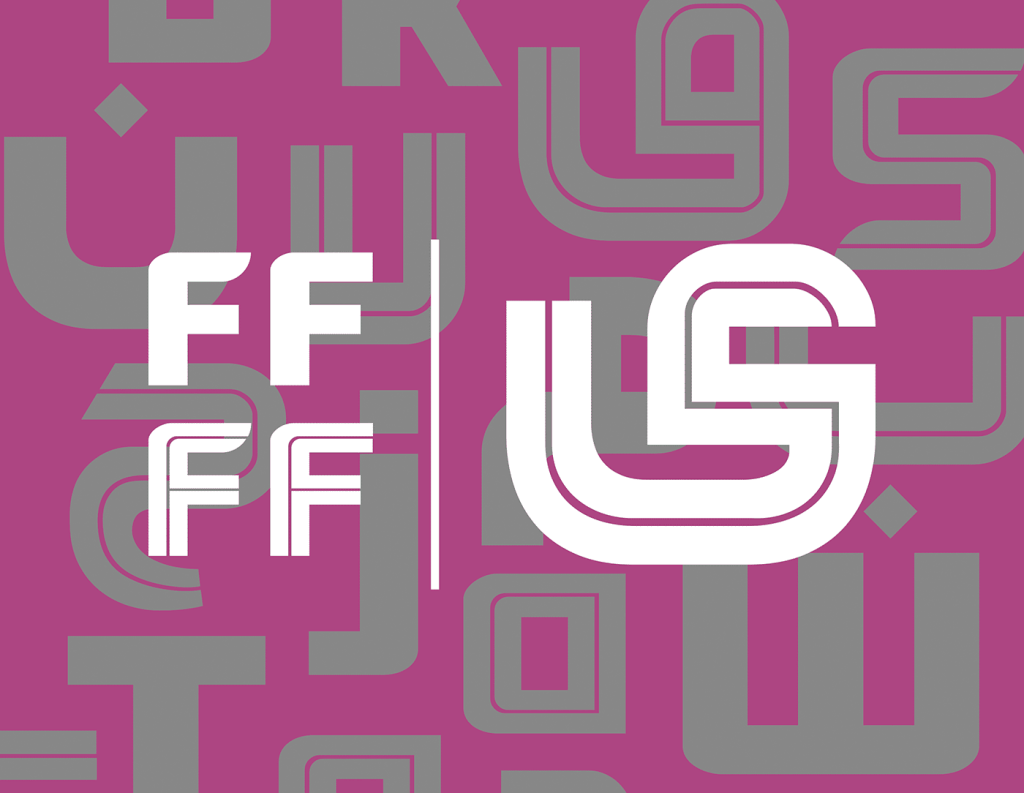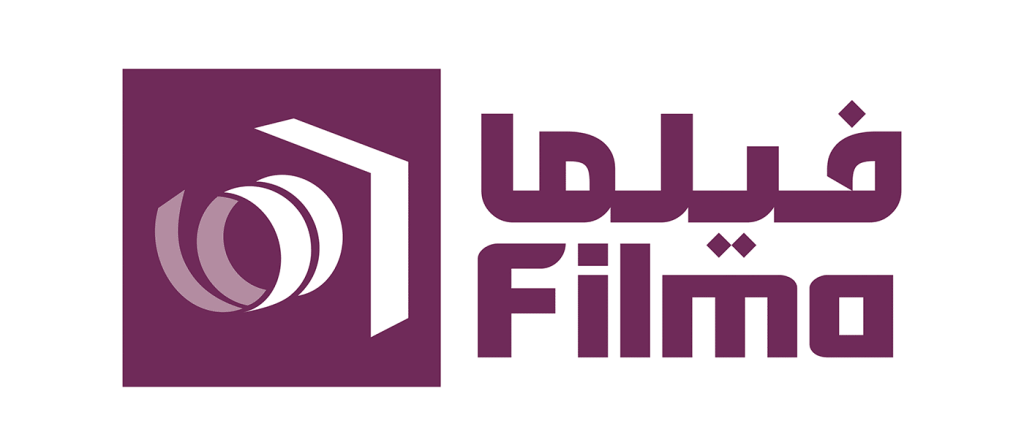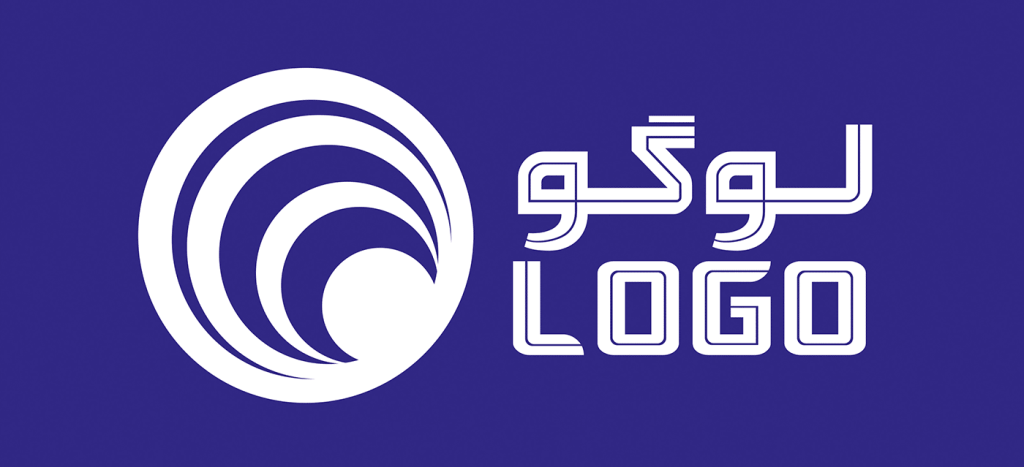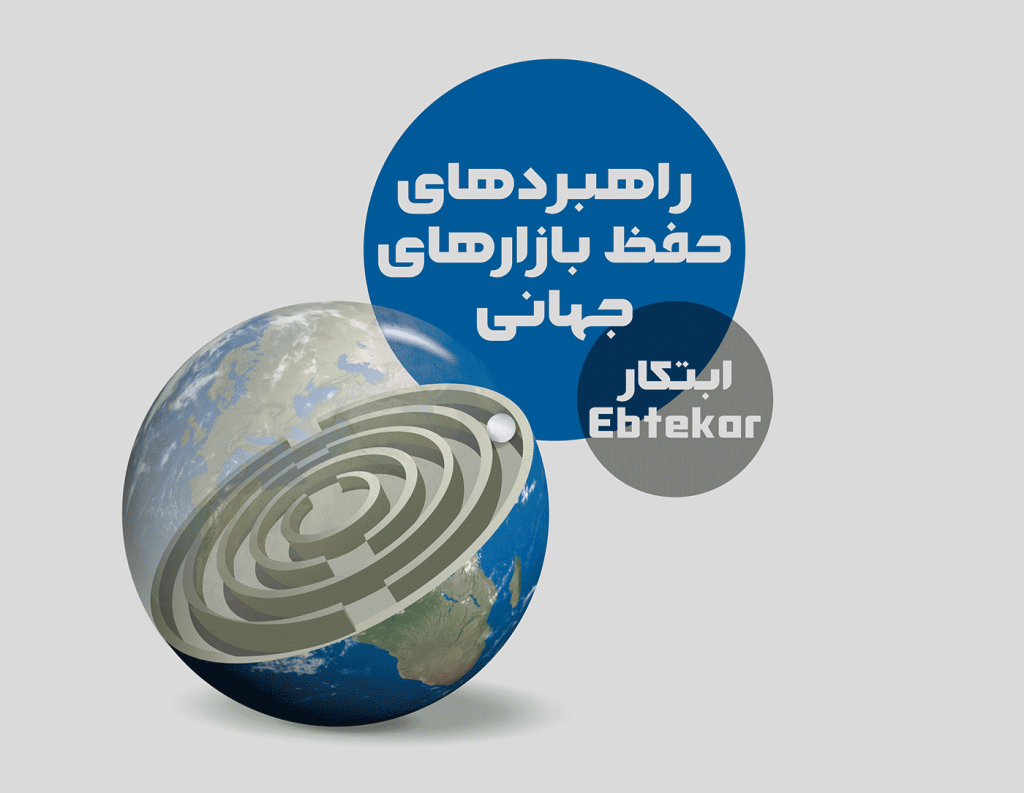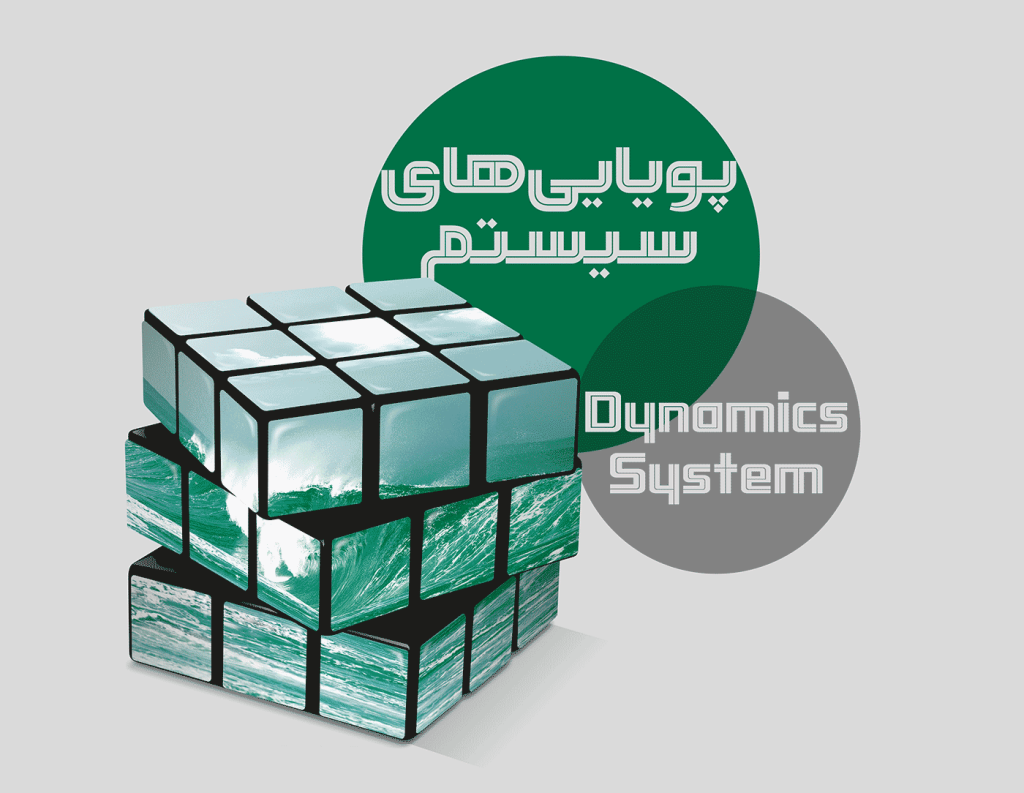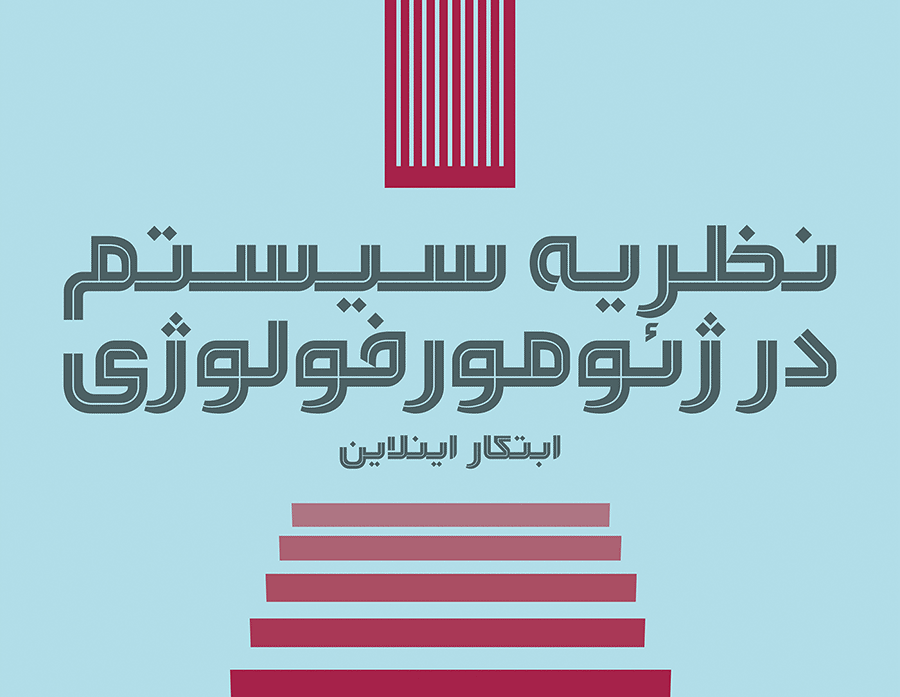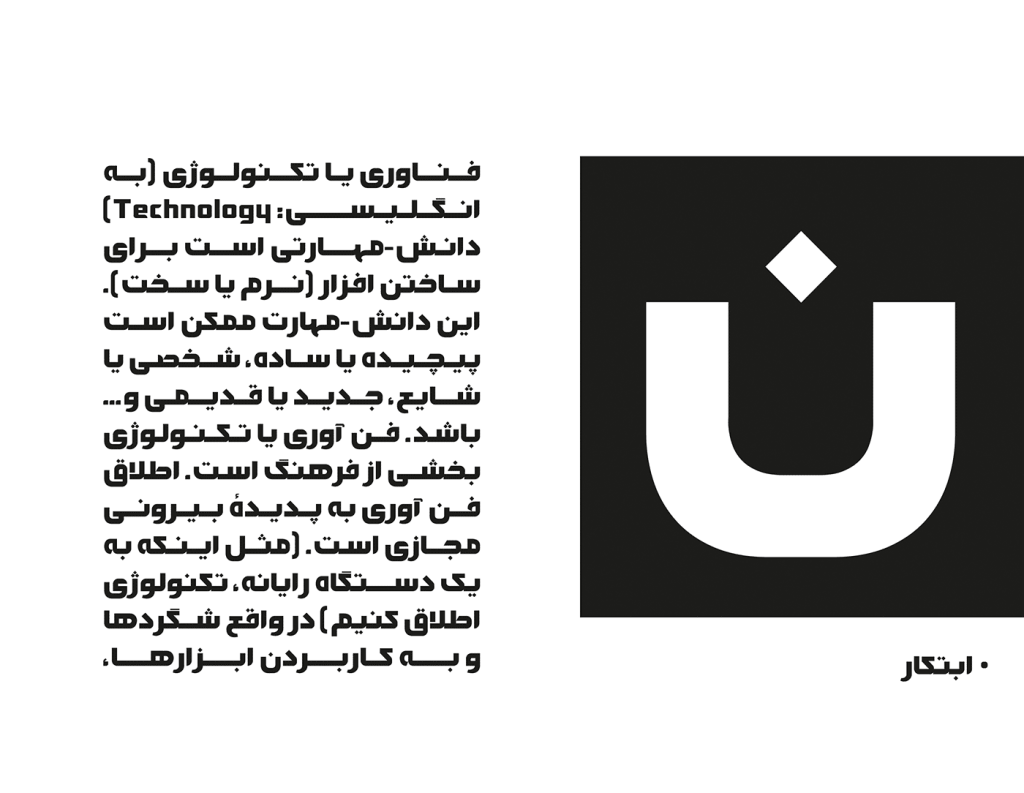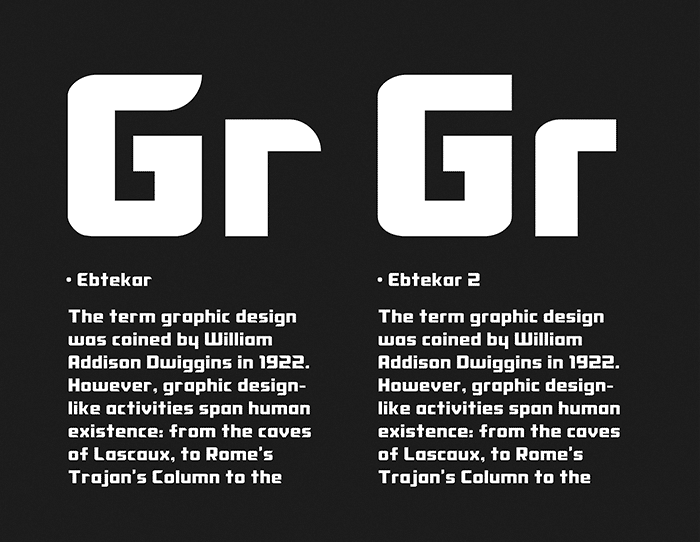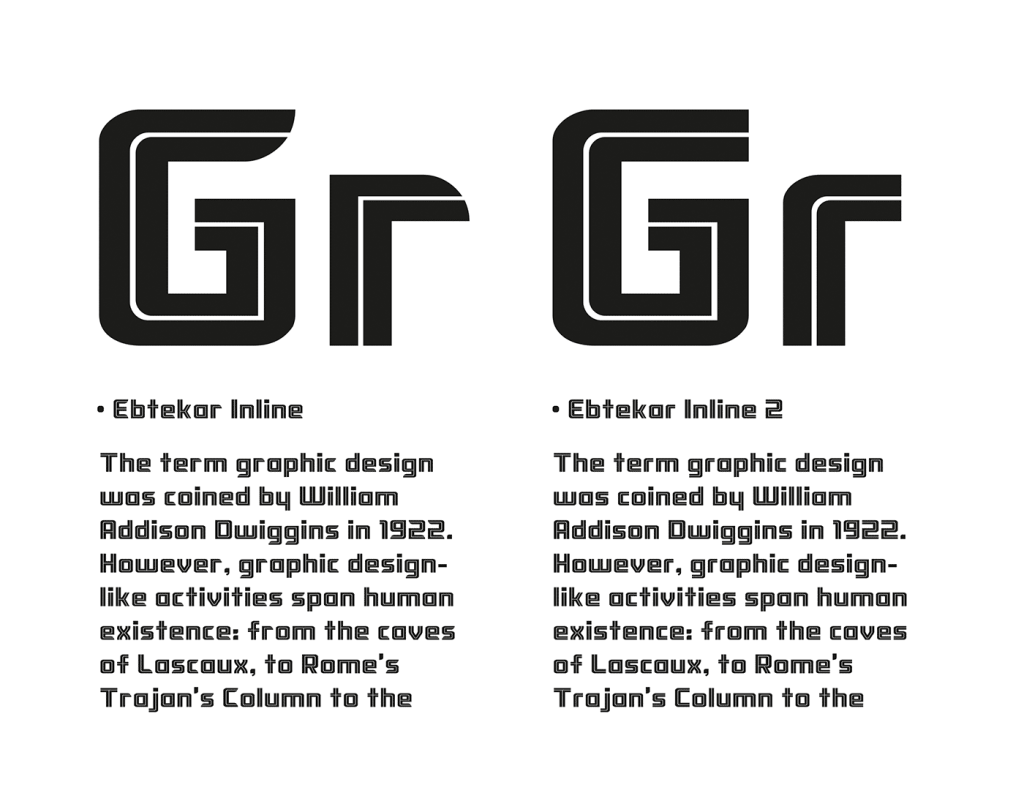
فونت ابتکار قلمی از خانواده هندسی
فونت ابتکار طراحی شده توسط آقای توسط آرمان خرمک از دسته تایپ فیس های خانواده هندسی است. این قلم با دارا بودن ویژگی های خاص و منحصر به فرد خود طرفداران و علاقه مندان زیادی دارد. ابتکار با دارا بودن 2 استایل ساده و تین لاین نیاز طراحان را در جنبه های مختلف مرتفع می سازد. دارای ویژگی نمایشی است از این جهت ساخته شده تا نگاه مخاطبین را به خود جذب نماید.
استایل ساده دارای فضای رسمی تر و جدی تری نسبت به مدل این لاین می باشد و مناسب فضاهای کلاسیک و آکادمیک می باشد . حال آنکه سبک این لاین این تایپ فیس ویژگی نمایشی بسیار بیشتر و شمایی تزئینی می باشد که برای تبلیغات در حوزه های مختلف از دنیای وب و دیجیتال گرفته تا صنعت چاپ مناسب است .
ابتکار در اصل نسخه فارسی شده فونتی لاتین می باشد که امروزه با تلاش و زحمات تایپوگرافان فونت فارسی تبدیل و بازطراحی شده است. یکی از ویژگی های منحصر به فرد این تایپ فیس، مشخصه مچ میکینگ است. یعنی در ترکیب حروف لاتین و فارسی هماهنگی نزدیک و فوق العاده ای وجود دارد،
ابتکار قلمی برای طراحی لوگو تایپ و پوستر
اما ابتکار قلمی چند زبانه و چند کاربره است این تایپ فیس مناسب متون کوتاه و عناوین و تیتر های تبلیغاتی و مطبوعاتی است . شما عزیزان می توانید در نرم افزار های طراحی مانند فتوشاپ، ایلسترتور و اینشات و .. با این قلم لوگو تایپ، جلد کتاب یا پوستر که دو زبانه هستند را ایجاد و طراحی نمائید.
فارسی ، انگلیسی ، عربی، پشتو و اردو
2 استایل
در پنج زبان لاتین، عربی، فارسی، پشتو و اردو قابل استفاده است.
این قلم دو حالت متفاوت دارد؛ معمولی و اینلاین. که البته در حالت لاتین دو سبک متفاوت وجود دارد که با نامهای Ebtekar 2 و Ebtekar_inline2 آنها را دریافت میکنید.